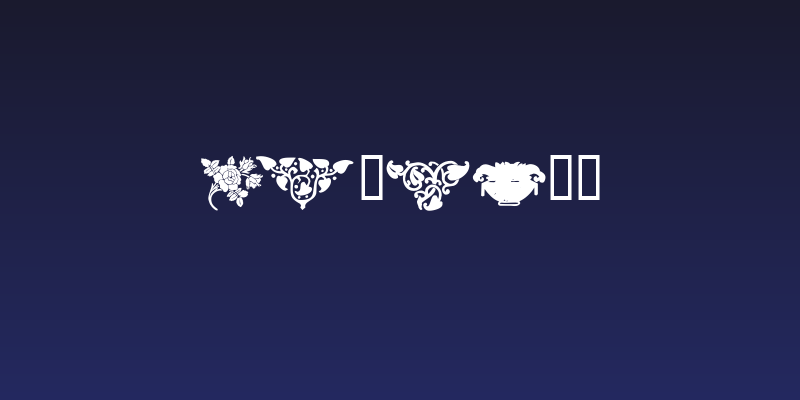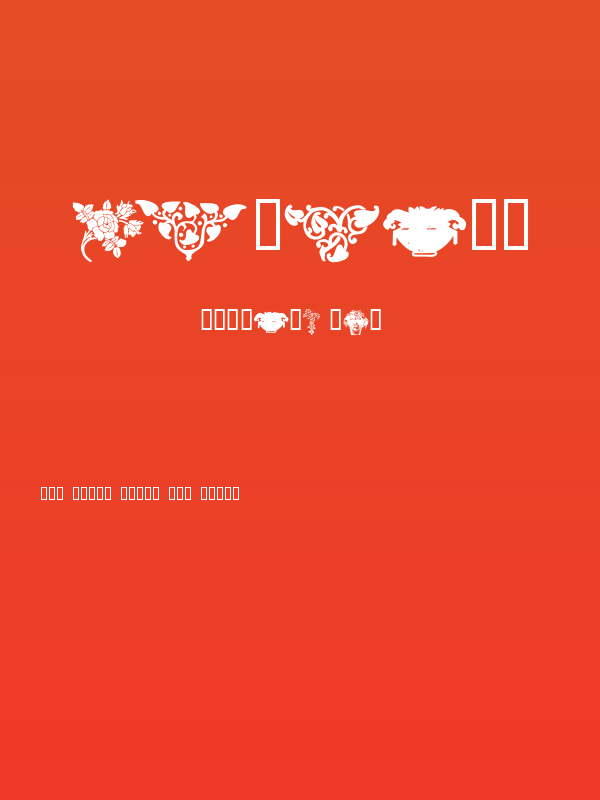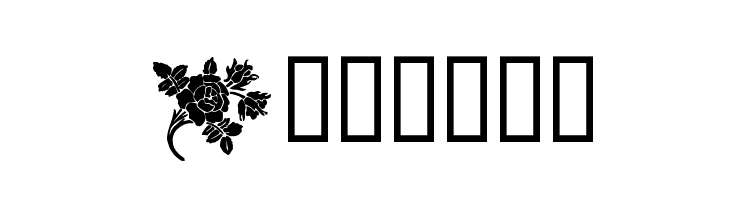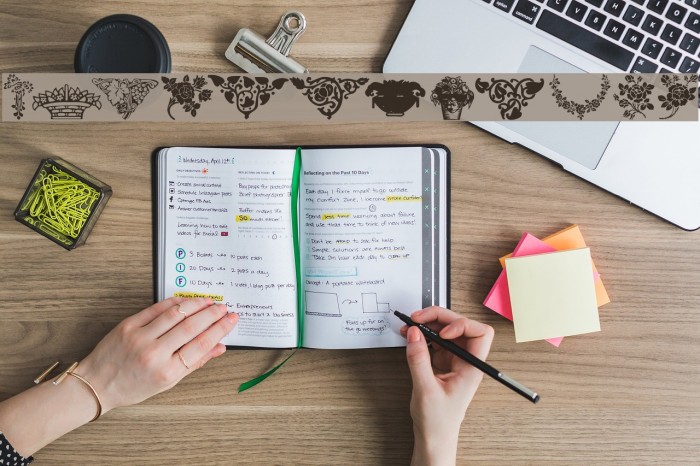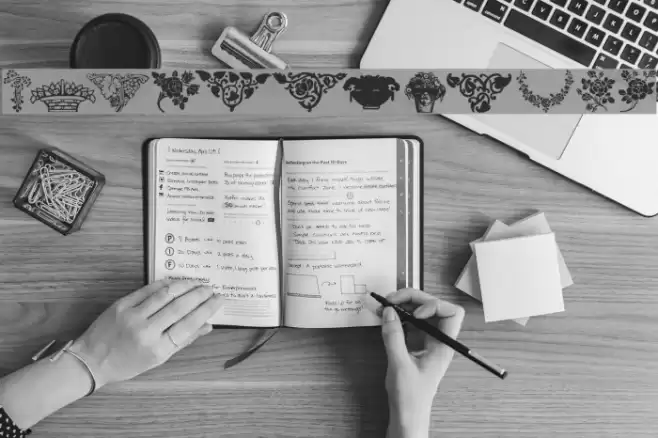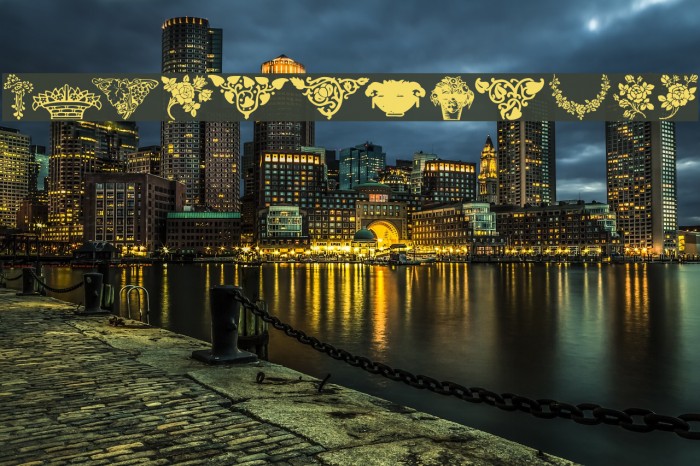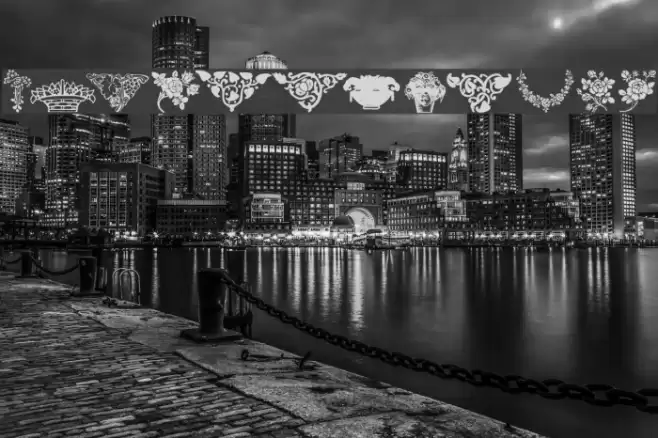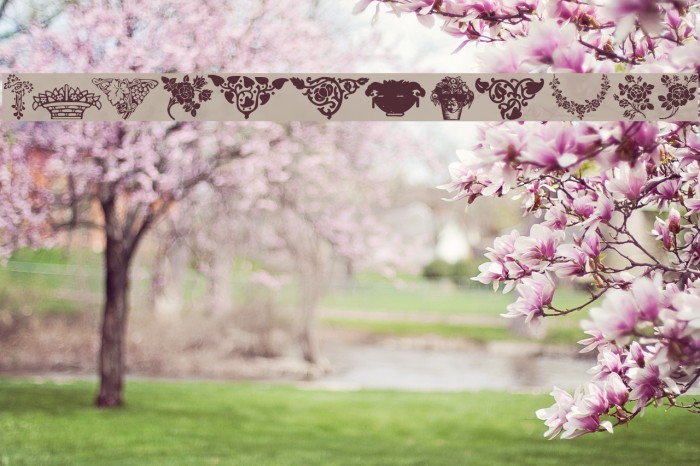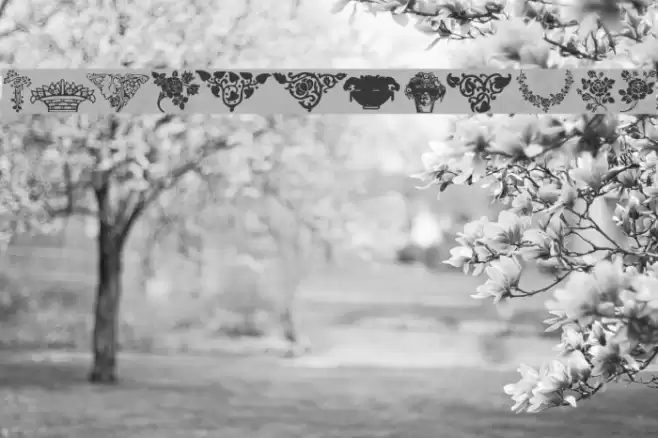
Design3 Font
✎ Retro
| Caso d'uso | Decorative elements, not suitable for text. |
| Progetti proposti | Ideal for use in decorative borders, invitations, greeting cards, or as embellishments in graphic design projects. |